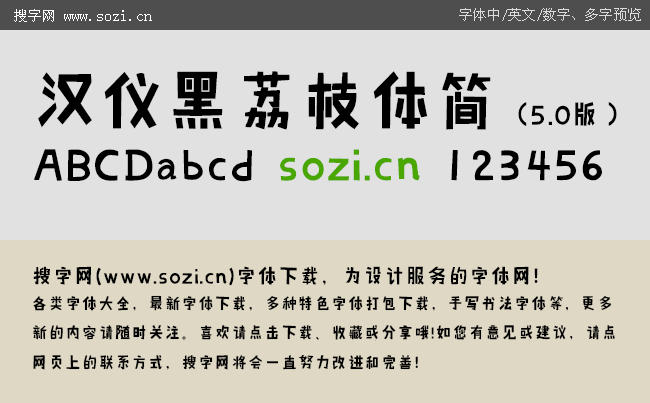
漢儀黑荔枝體簡
搜字網(wǎng)給大家提供一款漢儀字體公司出品很具童真的中文字體下載。很多小孩子在剛開始寫字的時候很喜歡寫這種線條棱角分明的文字,這種中文字體特點是沒有粗細變化,很實實在在童真的感覺。字體作者希望能體現(xiàn)出赤子之心,少年,希望,清澈純簡。這款中文字體繪本故事書,兒童讀物等適用,希望人們在使用字體的時候除了設計感,還能體會到這種童真童趣。